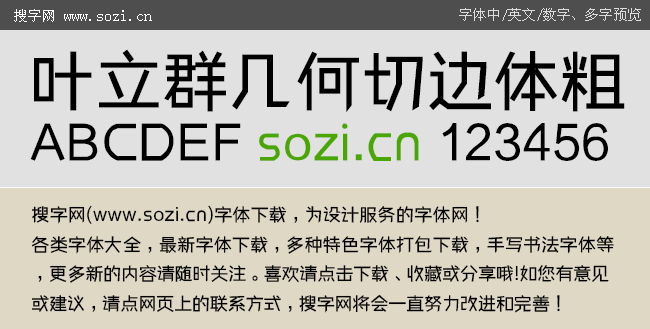
葉立群幾何切邊體粗
搜字網(wǎng)提供一款葉立群幾何切邊體粗中文字體下載,葉立群幾何切邊體粗是一款以黑體為原形設(shè)計(jì)的中文藝術(shù)字體,字體簡(jiǎn)潔漂亮,效果非常出色,適合應(yīng)用于廣告設(shè)計(jì)、名片設(shè)計(jì)、包裝印刷、產(chǎn)品設(shè)計(jì)等應(yīng)用。